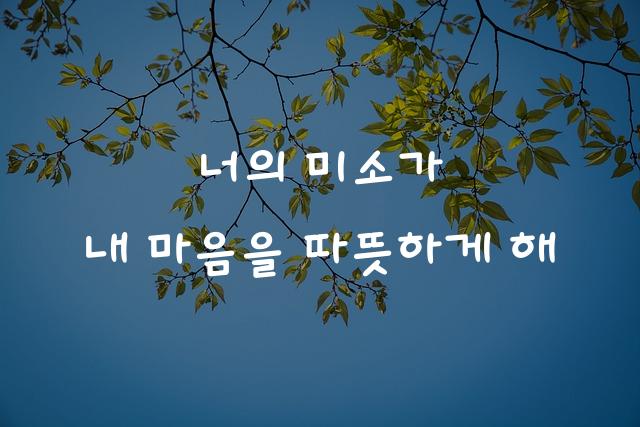
가비아 흘돋체는 독특한 형태의 장식체와 둥근 고딕 요소를 결합하여 유니크한 분위기를 제공합니다. 이 폰트는 모던함과 동시에 친근감을 느낄 수 있어 다양한 디자인에 활용하기 좋습니다.
가비아 흘돋체은(는)
기본 고딕, 둥근 스타일, 장식 스타일, 감성적인, 부드러움, 복실복실, 별모양/패턴 계열의 생김새를 가지고 있으며
초대장, 인사말 카드, 카페 메뉴 등에서 자주 활용되며, 효과적인 메시지 전달에 적합합니다.
이 폰트는 음식/식음료, 문화/예술, 이벤트/웨딩 분야에 잘 어울리며,
따뜻한, 감성적인, 부드러운 느낌을 담고 있는 것이 특징입니다.